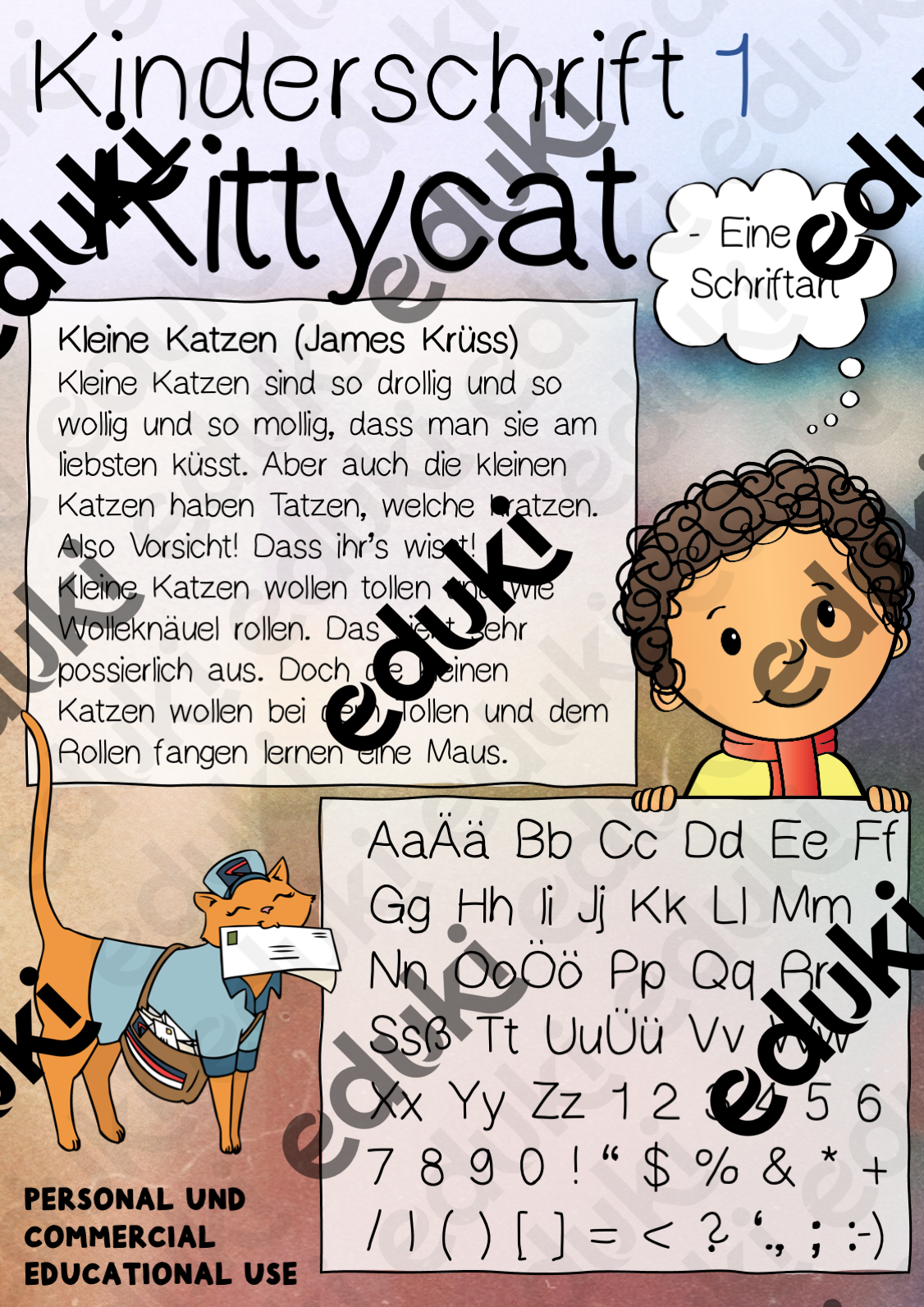
selbst erstellte Schriftarten - Kinderschrift 1 - KittyCat / Font - Quirlidoodle - Deckblatt
Eine süße Kinderschrift die eure Materialien definitiv bereichern kann und für das gewisse Etwas sorgt.
Kinderschrift 1 - KittyCat / Font